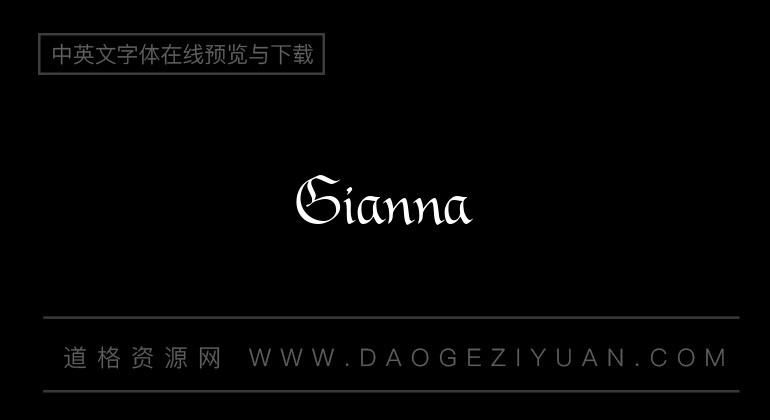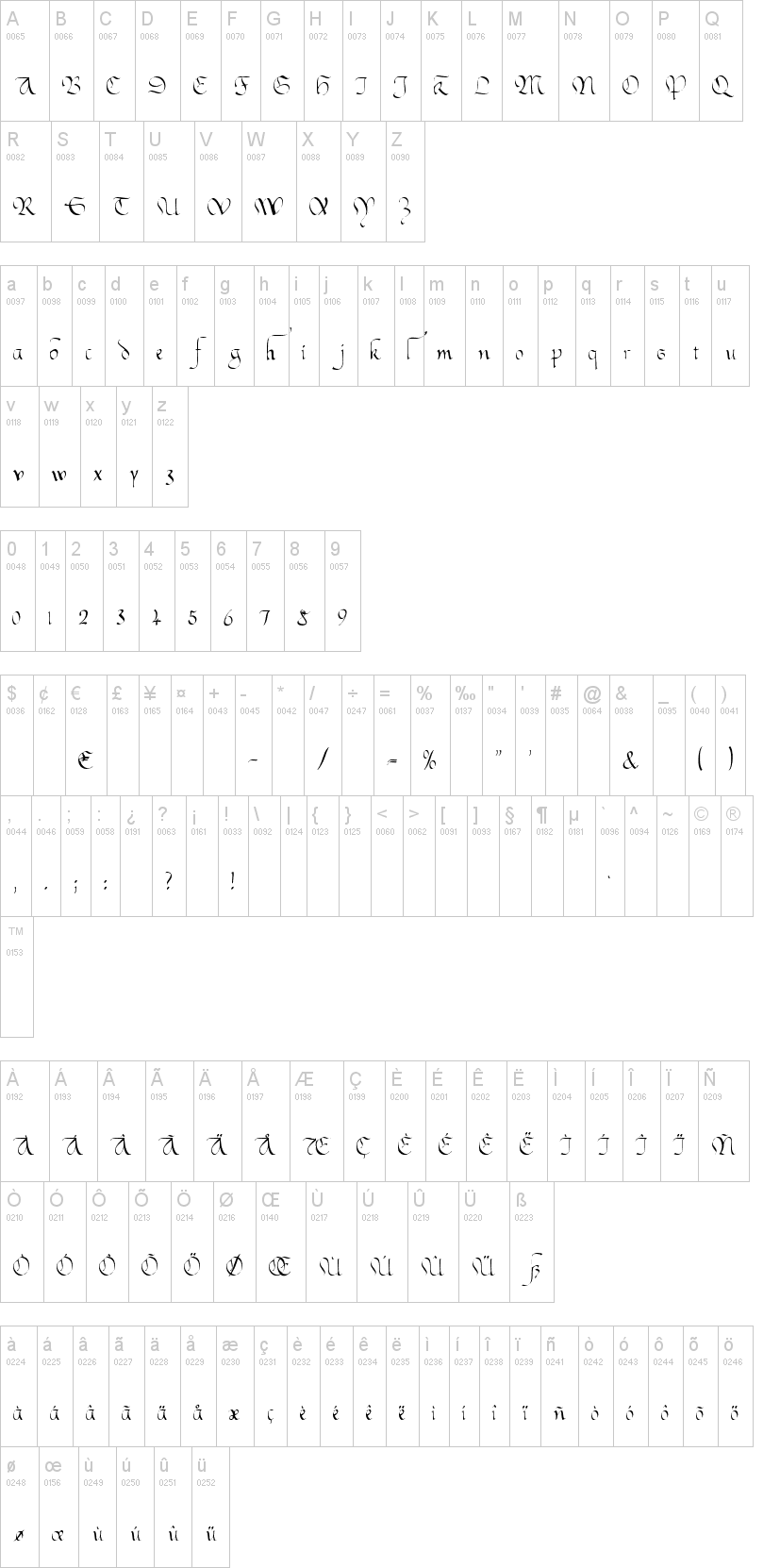
Gianna 是一种漂亮的手写风格字体。它的特点是非常流畅、自然,看起来非常舒适。Gianna 字体的设计非常注重细节,精致的笔画和优美的弧线使它看起来非常优雅有品味。这种字体非常适合用于卡片、海报、包装设计、广告等场合,给人们带来一种温暖、亲近、优雅的感觉。内容介绍
Gianna是一款非常不错的手写艺术字体,具有很好的视觉感,适合于文化类的宣传设计、商业类品牌的广告和产品包装设计以及个性化文字排版等较多场景。